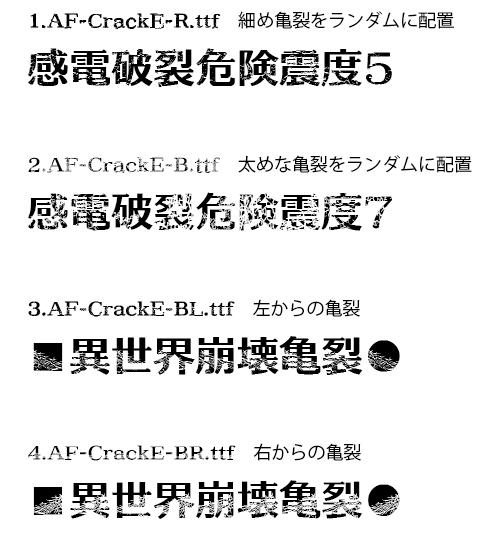
【収録書体】
本商品は下記4書体のセットです。
1)AF-CrackE-R.ttf 細め亀裂をランダムに配置
2)AF-CrackE-B.ttf 太めな亀裂をランダムに配置
3)AF-CrackE-BL.ttf 左からの亀裂
4)AF-CrackE-BR.ttf 右からの亀裂
AF-クラックは太めの明朝体をベースにひび割れた形状で危険を強調する為のデザインフォントです。大見出し、危険の強調、動画テロップやサムネイルへの応用にご検討ください。